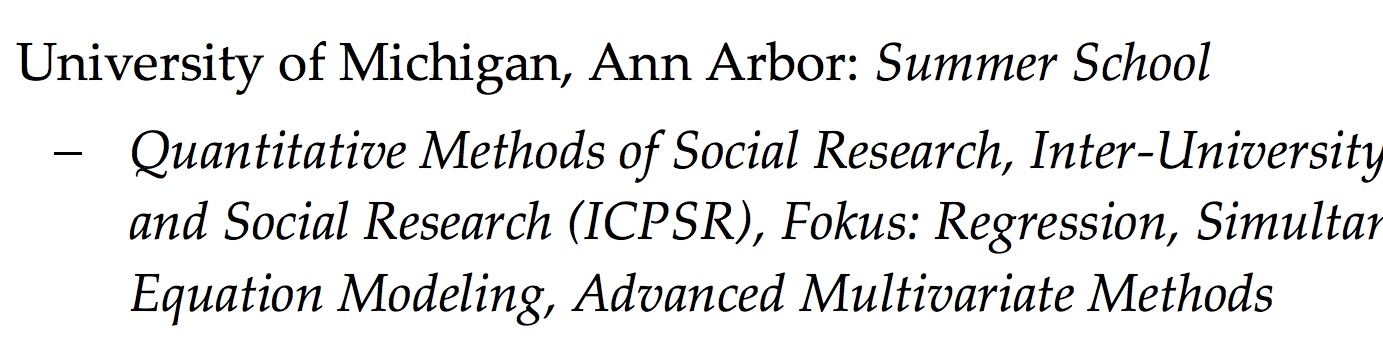
Suche mir unbekannte Schrift
Daher bitte ich Euch heute nochmals um Eure Hilfe mir bei der Identifizierung der nachfolgenden Schriftart zu helfen.
Da Palatino auf meinem Mac installiert ist, kann ich sie gleich benutzen. Super!
Das könnte ein LaTeX-Dokument sein? Dann wäre das mit großer Wahrscheinlichkeit die URW-Palladio. Die gibt es ganz umsonst bei jeder besseren LaTeX-Distribution und auch bei Artifex zum freien Download. Quelle:
:tuschel: Die Palatino ist bei Mac OS X integriert.
:tuschel: Die URW Palladio ist in vielen (allen?) LaTeX-Distributionen integriert. LaTeX wird sehr häufig für wissenschaftliche Dokumente verwendet. :tuschel:
Schon verstanden. Aber wie kommst Du hier auf dieses Thema? Km91 hat diese Schrift doch.
@bertel: Er schrieb, dass die Palatino bereits installiert ist, aber nicht woher er sie hat. Uwe kam mit einer LaTeX-Vermutung, worauf ich ihn einfach auf eine andere wahrscheinliche(re) Quelle aufmerksam machen wollte.
Weil es sein könnte, dass das Bild im Ursprungsbeitrag gar nicht die Palatino, sondern die Palladio zeigt, was ja Zapfs Umarbeitung der Palatino für URW war. Insofern ist der Hinweis schon okay.
Ich betrachte den Hinweis sogar als notwendig für die genaue Bestimmung der Schrift. Noch ein weiterer Hintergedanke: Nicht jeder hat auch MacOSX auf dem Rechner. Für die anderen Systeme kann man sich eine freie Version (GPL) beschaffen ohne dabei gleich kleinkriminell zu werden oder (unter Umständen nicht vorhandenes) Geld auszugeben.
Eigentlich ist eine Schrift (typeface) eine Schrift. Hier haben wir eine Palatino. Die Digitalisierung einer Schrift (font) ist was anderes. Ob wir hier eine LT Palatino oder URW-Palladio haben ist für mich leider nicht erkennbar. Schaut mal auf die Alternativen zur Palationo bei myfonts: https://www.myfonts.com/fonts/linotype/palatino/alternate_cuts.html
Nicht jeder hat auch MacOSX auf dem Rechner.